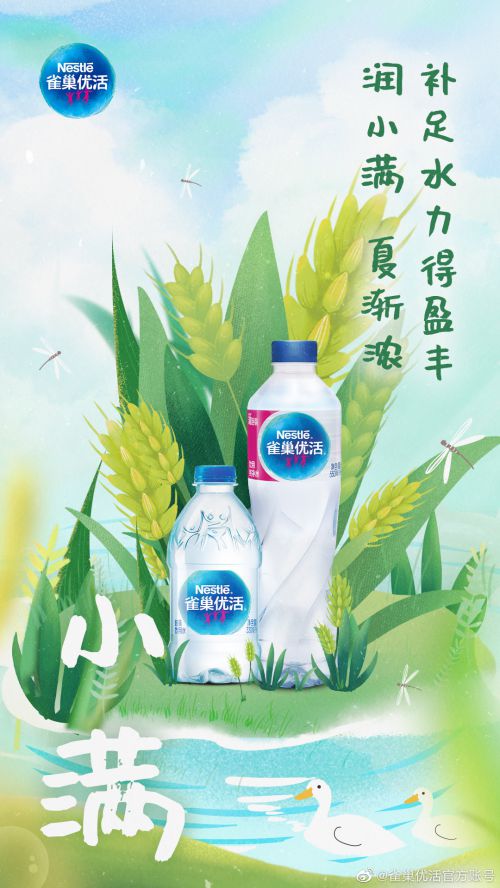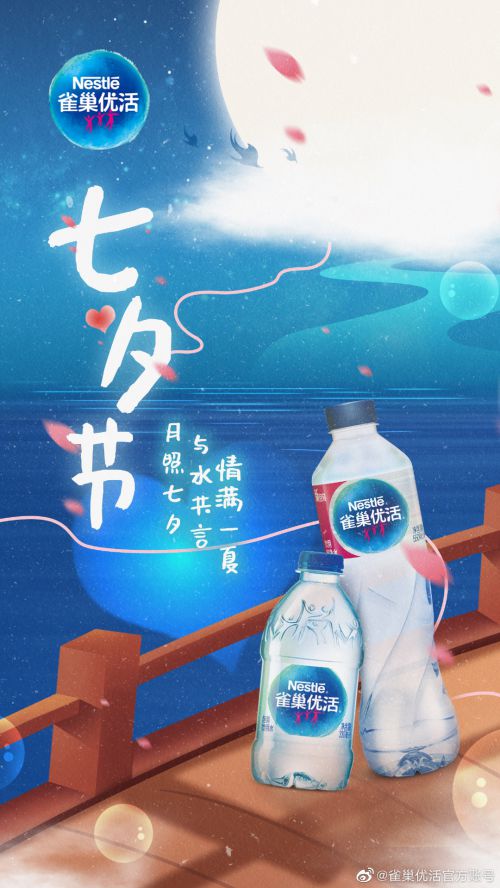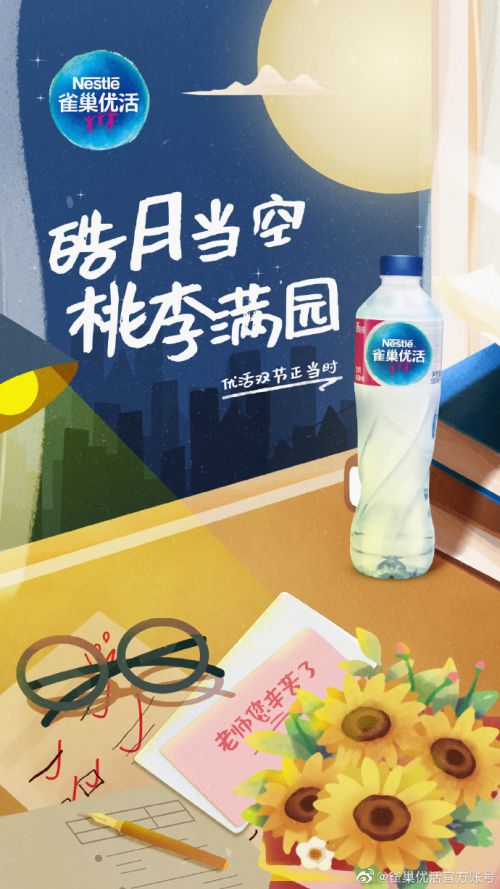
沐瑶软笔手写体
沐瑶软笔手写体是一款兼具卡通趣味与端庄优雅气质的手写体字体,以灵动手写风为核心,适配多元设计场景。字体支持简体中文常规字符集,授权范围为免费商用,满足个人与商业项目的字体使用需求,是设计爱好者与创作者的实用之选。 沐瑶软笔手写体在字形结构上展现出独特美感:修长的字型形态搭配居中的重心与适中的中宫,整体视觉平衡且舒展,既不过于紧凑也不显松散。笔型融入圆润弧度设计,圆头笔画搭配均匀的粗线条,让字体自带温暖柔和的质感,卡通风格与手写趣味自然融合,避免了传统手写体的呆板感。 值得注意的是,沐瑶软笔手写体采用笔画断开的连接方式,保留手写书写时的自然停顿感,使每一笔都似随笔尖流转而生,灵动又不失端庄。无论是用于海报标题、包装设计,还是手账排版、社交媒体配图,沐瑶软笔手写体都能以其可爱又优雅的气质,为作品增添独特的手写温度与设计巧思。